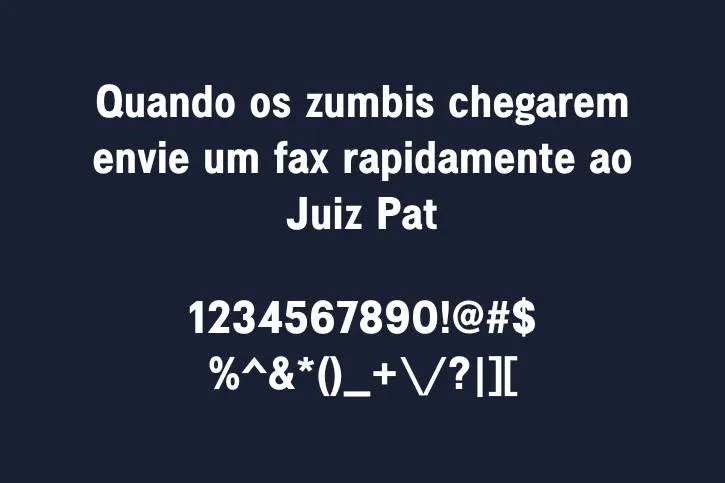
A fonte Penny Lane é uma fonte sem serifa derivada de placas de ferro fundido do século XX exibindo nomes de ruas de Liverpool projetadas por Keith Bates e publicadas pela K-Type. Está disponível em 5 pesos elegantes. Embora as letras usadas para placas de rua vintage variem em largura e estilo, o Penny Lane Bold semicondensado é bastante típico.
A cintura de letras como X e Y é posicionada na linha média, o que pode parecer incomumente alta. O G não tem uma barra transversal, e caracteres pontiagudos como o Z podem parecer discordantes com as formas geralmente grotescas das letras. Também é perfeito para combinar com uma Fonte Guess Sans que tenha textura e estilo semelhantes.
Além disso, oferece excelente legibilidade, mesmo em tamanhos menores. Seus caracteres bem desenhados e espaçados facilitam a leitura do texto em qualquer contexto, garantindo uma experiência de leitura agradável ao público-alvo. Sua ampla gama de pesos e estilos o torna uma escolha versátil.
Recurso Principal da Fonte Penny Lane
As principais características são a elegância e sofisticação. Projetada com traços limpos e precisos, esta fonte transmite uma sensação de modernidade e estilo. Sua variedade de pesos e estilos também o tornam uma escolha versátil para uma variedade de projetos de design.
Disponível em uma variedade de espessuras e estilos, essa fonte pode ser facilmente combinada com outras fontes, como a fonte Bomber TV. Além disso, oferece excelente legibilidade, mesmo em tamanhos menores. Seus caracteres bem desenhados e espaçados garantem que o texto seja facilmente compreendido.
Família de Fontes Penny Lane
- Penny Lane Bold Italic
- Penny Lane Bold
- Penny Lane Corroded Bold
- Penny Lane Italic
- Penny Lane Regular
Aplicações da Fonte Penny Lane
- Cabeçalhos de sites e blogs com um toque moderno e elegante.
- Materiais promocionais, como cartazes e banners, para chamar a atenção.
- Convites de eventos, dando um ar sofisticado aos detalhes.
- Logotipos e marcas, transmitindo uma sensação de contemporaneidade.
- Materiais impressos, como cartões de visita e folhetos, para destacar informações.
- Design de embalagens, proporcionando uma estética diferenciada.
- Redes sociais, criando posts visualmente atraentes.
- Projetos de design de interiores e decoração, para personalizar elementos.
- Em combinação com a Fonte Lucita, você pode criar apresentações, transmitindo uma imagem moderna.
- Publicações digitais e impressas, mantendo uma estética consistente.
Perguntas Frequentes!
Qual é a fonte da fonte Penny Lane?
É uma fonte sem serifa derivada de placas de ferro fundido do século 20 projetadas por Keith Bates.
Qual é a principal característica da fonte Penny Lane?
A cintura de letras como X e Y está posicionada na linha média, que pode parecer incomumente alta.